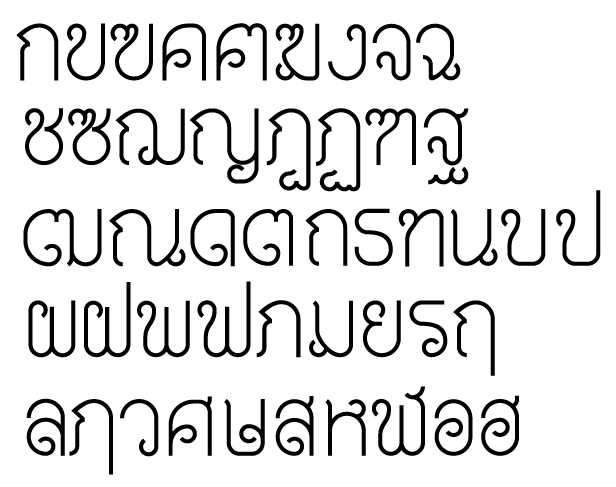
ชอบตัวนี้มากๆ ถึงมากที่สุดค่ะ
มีแพลนจะทำมาปล่อยมั้ยคะ
ตัวนี้ถ้าชอบ สามารถทำปล่อยได้ทันทีครับ เพราะว่าไฟล์ยังอยู่
แต่ต้องแก้ความหนามันเพิ่ม
แล้วก็ต้องแก้หาง น หนู ให้หลบในด้วยจะได้ไม่มีปัญหาเรื่อง kerning ครับ
เจ้าตัวนี้เป็นคาแรคเตอร์ที่ใช้ประจำเวลาอยู่มหาลัย มันชื่อตัว แห ครับ
ชอบหน้าของตัวแหอะ
สนับสนุนเต็มที่เลยค่ะ ชอบมากจริงๆนะ
แบบนี้พอไหวไหมหว่า
จริงๆก็คือเอาฟอนต์เก่ามาเติมหัวนั่นแหละ
แต่ scale มันไม่เท่าของต้นฉบับผมเลยว่ามันแปลกๆ
รู้สึกหัวจะใหญ่เทอะทะไปนิดนึง
เดี๋ยวผมว่าจะลองลดขนาดดู
คิดอีกทีไม่ลดดีกว่า เห็นชัดดี ( แต่เปลี่ยนโครงสร้างหน่อยนะครับ )
ข ฃ แคบกว่านี้อีกนิดน่าจะดีนะครับ
รออย่างใจจดใจจ่อค่ะ สู้ๆ
ลองดูนะครับ ผมตั้งกฎเพิ่มว่า ให้พยัญชนะแต่ละตัว มีกลมๆได้แค่ตัวละวงเท่านั้น
( ไม่งั้นมันนัวเนียมาก
)
ลองพิมพ์ ขบปฃ ให้ดูหน่อยนะครับ
พิมพ์ ข ขวด ไม่ได้ครับ
ปรับ บ ป ให้เหลี่ยมกว่านี้ดีกว่าเนาะ
แก้และ
ต๊าย ไม่เคยพบเคยเห็น มีคนทำฟร้อนมาโชว์ในห้องแสดงงานด้วย น่ารัก
ส่วนตัวชอบหัวพวก ล ส อ ฮ ษ แบบเดิมค่ะ
แบบตัวนี้ดูแล้วชอบไปหมดเลยจริงๆนะ คือชอบชุดเดิมมากกว่าน่ะค่ะ
แยก ข กะ บ ค่อนข้างลำบากแฮะ
ทำไงดีเนี่ย
ทำใหม่